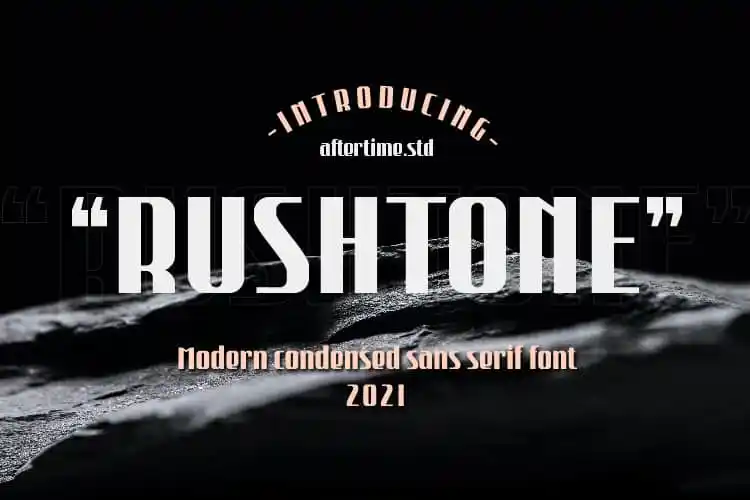
RUSHTONE – Sans Serif Font – Download Grátis
A fonte RUSHTONE – Sans Serif oferece uma opção ideal para projetos variados, tanto grandiosos quanto delicados, proporcionando estilo e elegância à sua obra. Seja você um designer de luxo criando selos de marca ou uma editora desenvolvendo capas de livros, a RUSHTONE é perfeitamente adaptada aos seus objetivos. Sucesso em sua próxima campanha de moda feminina ou em sua loja de beleza pode estar ao alcance com essa fonte moderna e sofisticada. Ela também se adapta perfeitamente para card inviites, artigos de citação, decorações domésticas, selos e até mesmo eventos especiais como casamentos e aniversários. A RUSHTONE é sua font de eleição para estilos diversos, sem que você precise recorrer a mais de um tipo de letra.